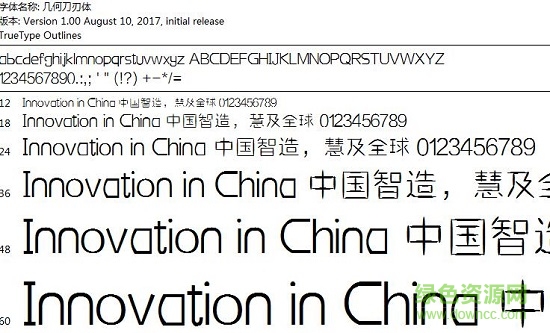
幾何刀刃體ttf是一款可以直接用來進(jìn)行藝術(shù)創(chuàng)作的中文字體,字體整體呈現(xiàn)黑體字體的特色,視覺效果鮮明,并且還有些許的不規(guī)則帶來幾分俏皮的感覺,喜歡的朋友歡迎下載!
幾何刀刃體ttf是一款獨(dú)具魅力的幾何字體,這款之刃的邊角就像是非常筆直光滑,橫劃的處理顯得格外的有意思,整體效果在整齊中帶著幾分不規(guī)整,適合用來進(jìn)行設(shè)計(jì)!